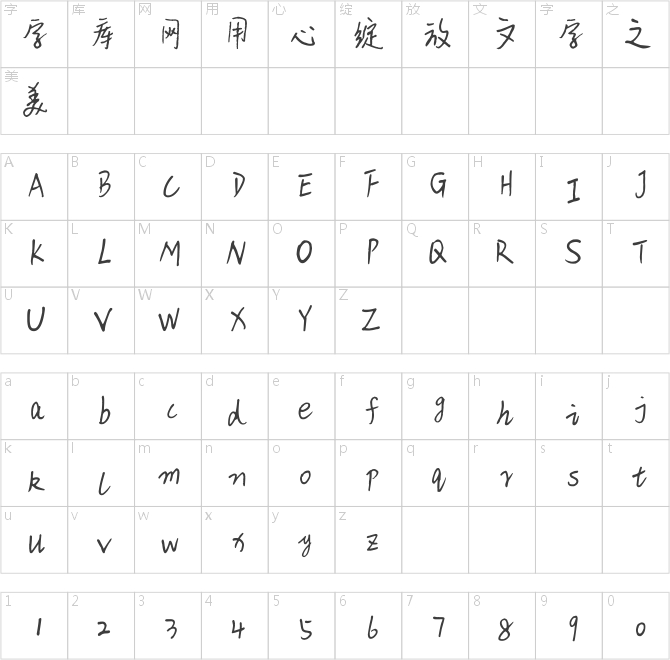
新葉念體 詳情頁
念是惦記,是想念,是思念,是牽掛。手寫字有著強烈的人文氣息,不管身在何處,請告訴遠在家鄉(xiāng)的父母,我很好;不管彼此離的有多近,請告訴你的那個TA,我愛你!紙短情長,見字如面。
從書寫到掃描、調(diào)整,編碼入庫,再調(diào)整,整個過程很冗長。漢字的字庫開發(fā)數(shù)量龐大,開發(fā)過程中個別字體可能不夠精細,望見諒。新葉念體采用GB2312編碼,約6900字,您可以免費商用。您還可以關(guān)注我們的微信公眾號:新葉傳媒,更多字體我們將擇日上線。